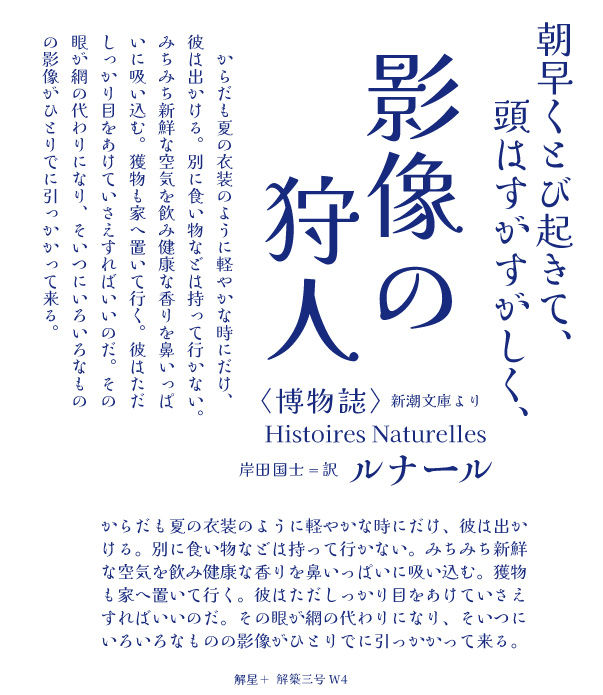
解仮名- 解築三号 Set-kaisei
◉ Google Fonts Kaiseiの各Weightに対応した仮名フォントの紹介です。(W4=Regular,W5=Medium,W7=Bold,W8=ExtraBold) 合成フォントとして使用可能です。
Kaisei(解星)はhttps://fonts.google.com/?query=Font-Kaiからダウンロードできます。◉築地活版製造所のこの平安調書風をしのばせる細い三号仮名は、同様の一号とともに多く使われました。楷書などとも組まれています。書を日常とした先人たちは、連綿する書の息吹の中から一字一字を独立した正方形の金属字形として見事に誕生させました。「解築三号細かな」は、築地活版製造所の三号仮名を基に明朝体や楷書など現代の電子組版状況と違和感無くお使いいいただけるように仮名の比率や濃度バランスを調整しています。汎用性の高い身近な書体としてお使い頂けるよう翻刻しました。